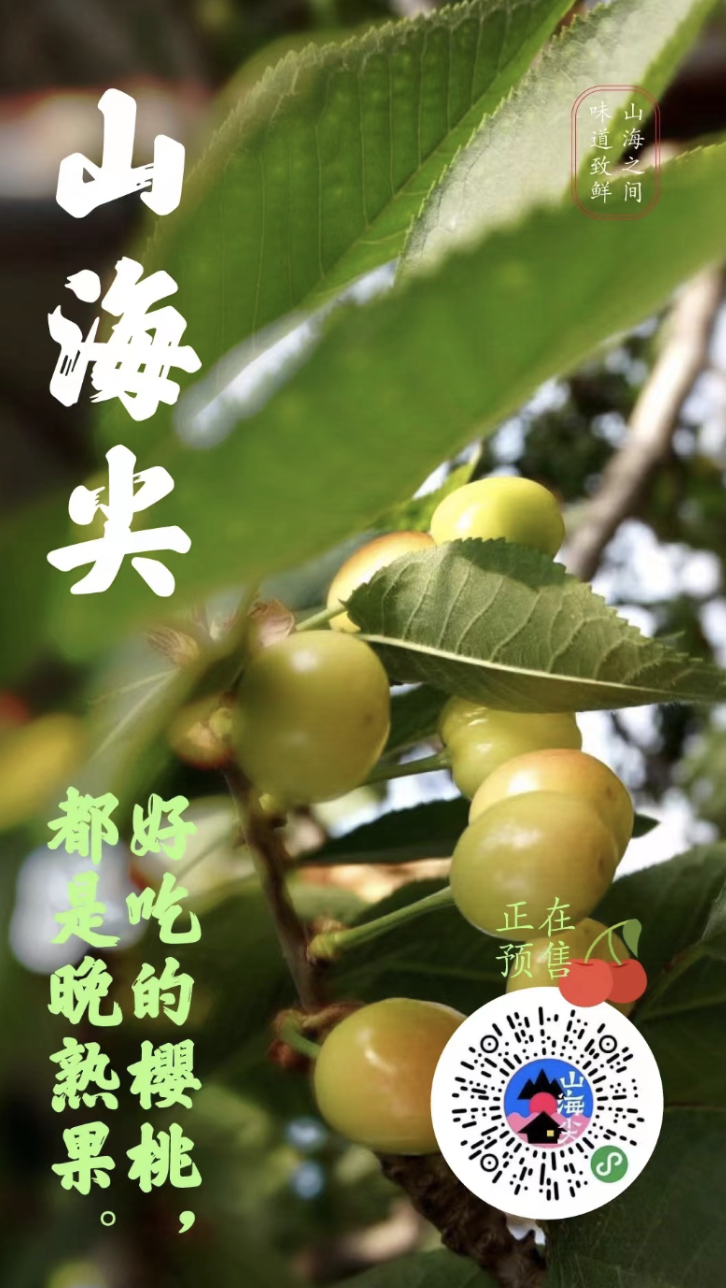
方正马克体
何德林
创意字体
方正马克体是一款融合了手绘POP的创意字体。书写果断,充满活力,意趣十足。整体风格新颖可爱,特色鲜明。适用于餐饮类产品包装设计,商业类趣味广告和新媒体宣传设计。
何德林
90后平面设计师,方正字库签约设计师,
开发创作了《方正马克体》、《方正翘萌体》、《方正字迹-青柠体》和《方正手迹-猪猪体》四款字库产品。